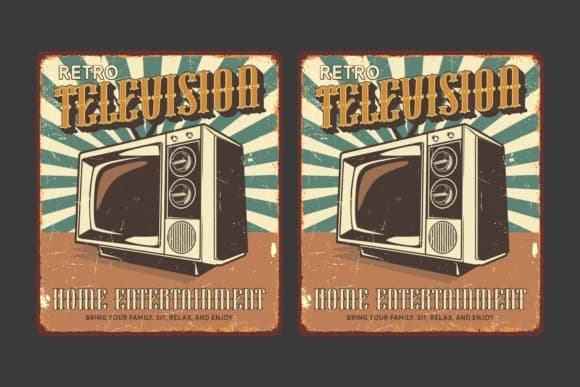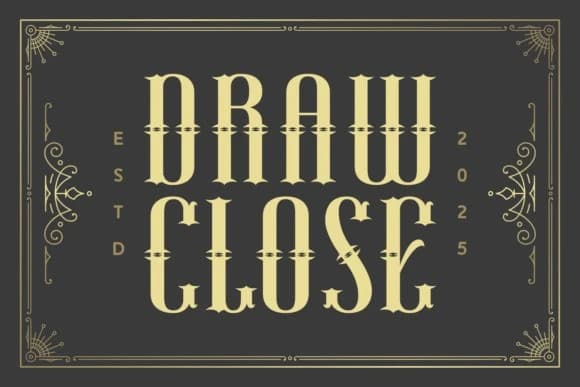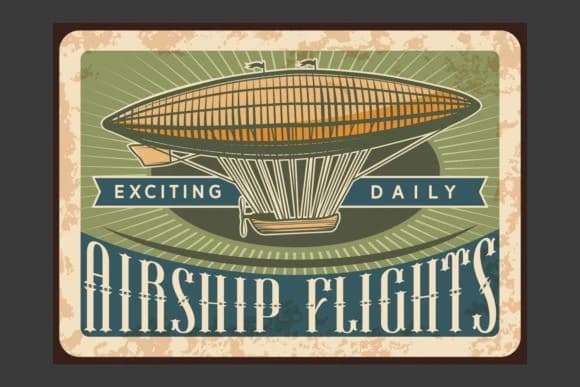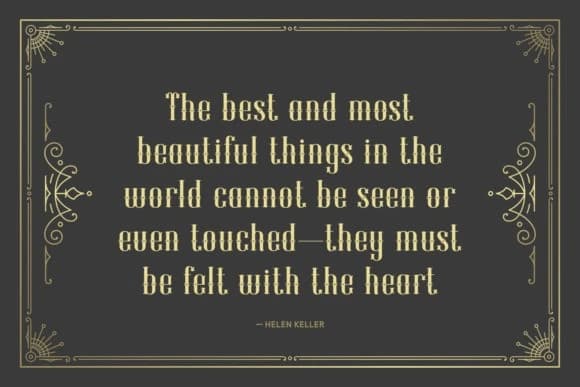
Draw Close Font, Blackletter ile Vintage sanatının kusursuz bir birleşimi. Bu titizlikle tasarlanmış yazı tipi yalnızca metin için bir araç değildir, aynı zamanda keyifli bir görsel deneyim de sunar. Bir dizi farklı uygulama için mükemmel.
Draw Close Font, Blackletter ve Vintage sanatlarının kusursuz bir birleşimi. Bu özenle tasarlanmış yazı tipi yalnızca metin için bir araç değildir; aynı zamanda keyifli bir görsel deneyim sunar. Bir dizi farklı uygulama için mükemmeldir.